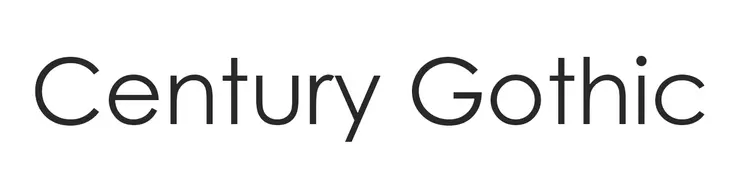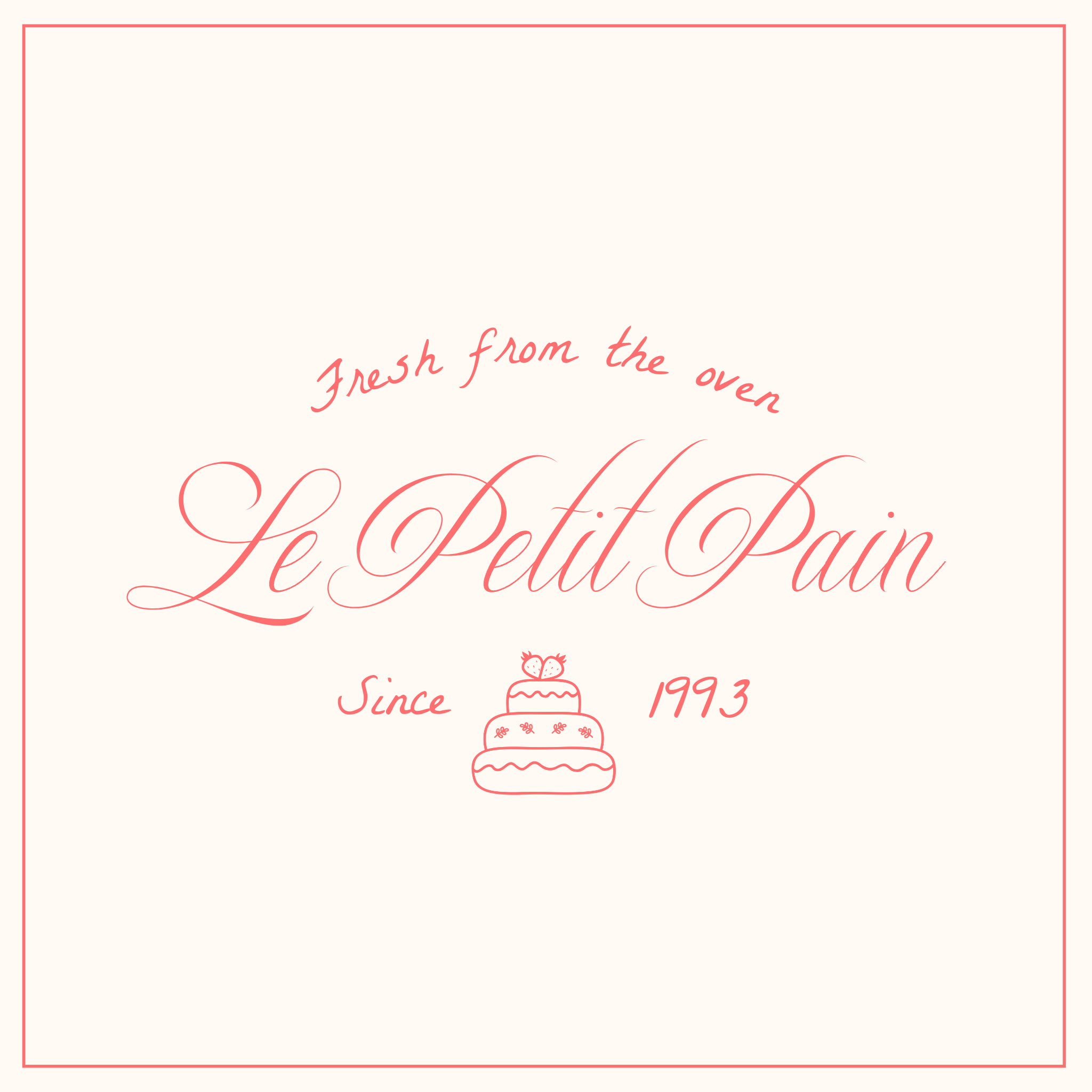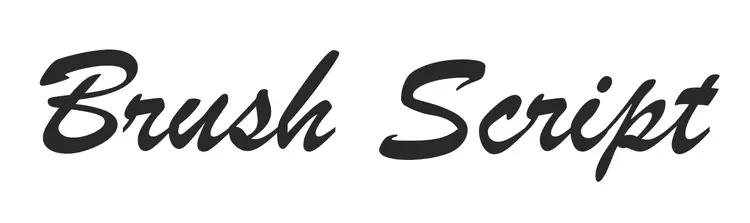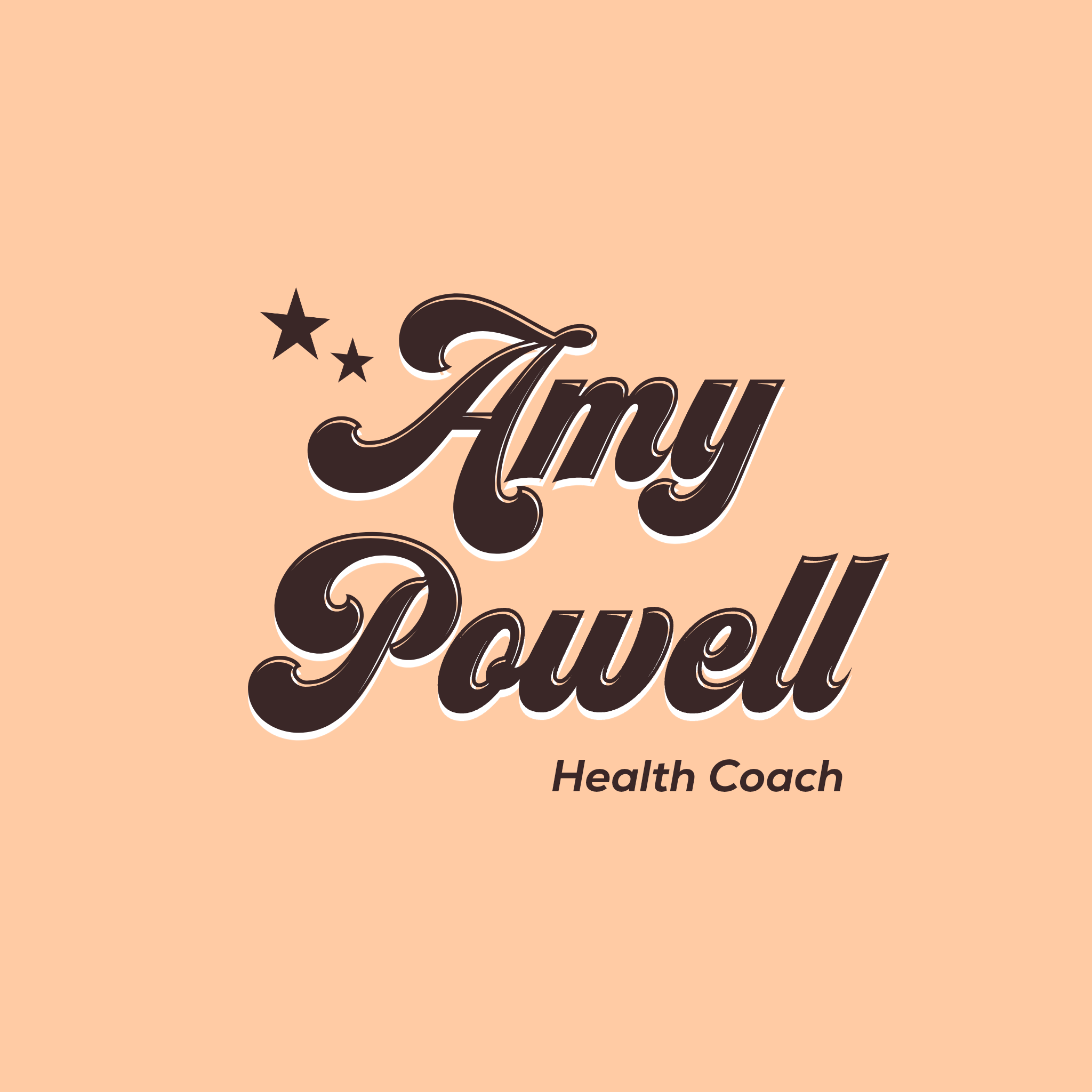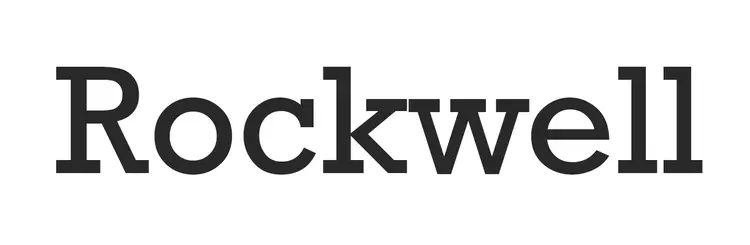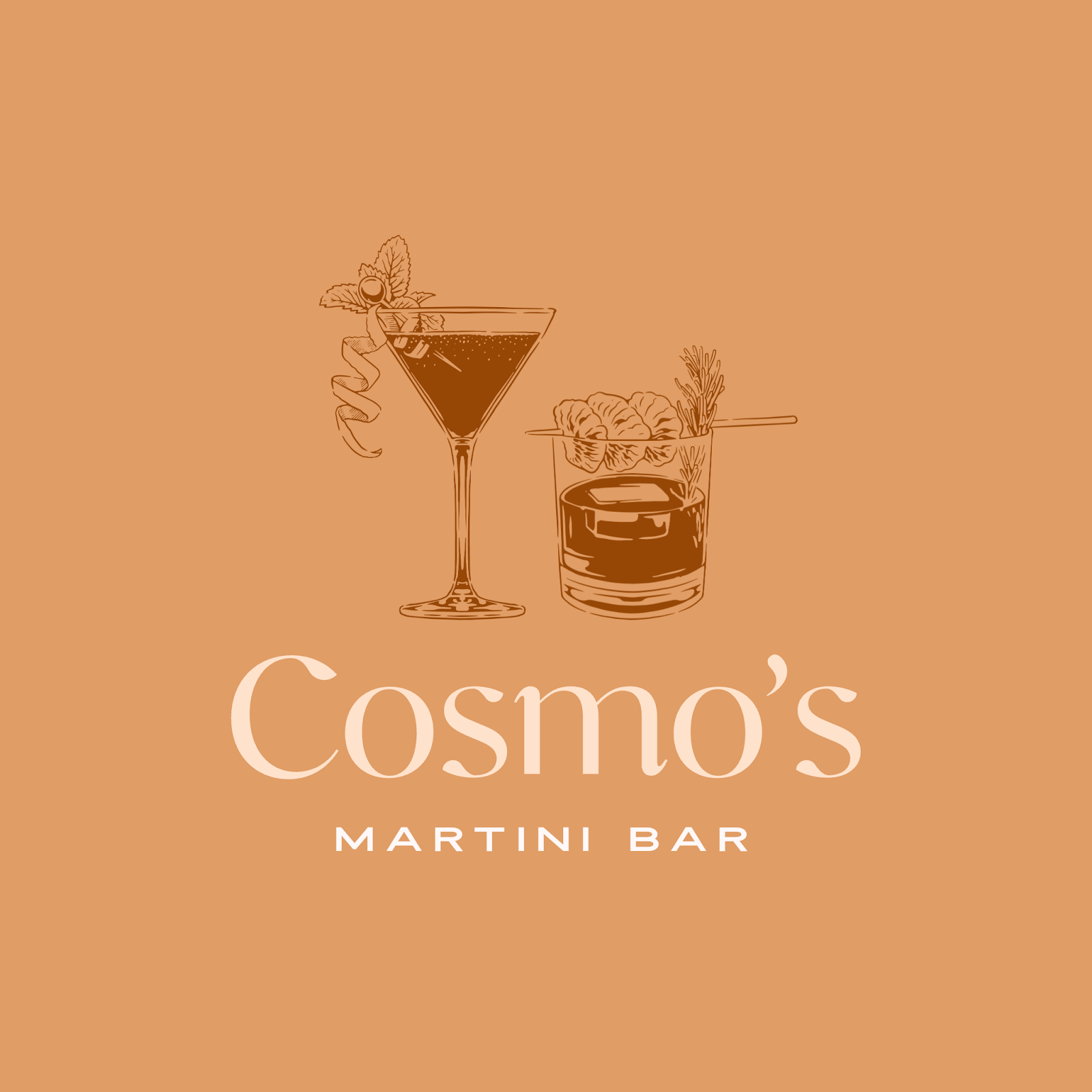
Crear un logo que se quede en la mente de las personas es clave para construir una identidad de marca sólida, y uno de los elementos más importantes para lograrlo es la tipografía.
Elegir la fuente adecuada puede transformar tu logo, hacerlo más reconocible y transmitir el mensaje correcto sobre tu marca.
En este artículo, te compartimos 40 de las mejores tipografías para logos y te damos algunos consejos para que elijas la que mejor se adapta a tu negocio. Ya sea que busques una fuente con estilo clásico, algo moderno o un diseño más artístico, aquí encontrarás un montón de ideas para inspirarte.
Los 4 tipos principales de familias tipográficas empleadas para el diseño de logotipos
Cuando diseñamos un logo, hay cuatro tipos principales de tipografías a considerar: serif, sans serif, script y display. Cada una tiene sus propias características y transmite emociones o ideas diferentes.
A continuación, te explicamos cada tipo con diez ejemplos populares dentro de cada categoría.
Tipografías serif para logos
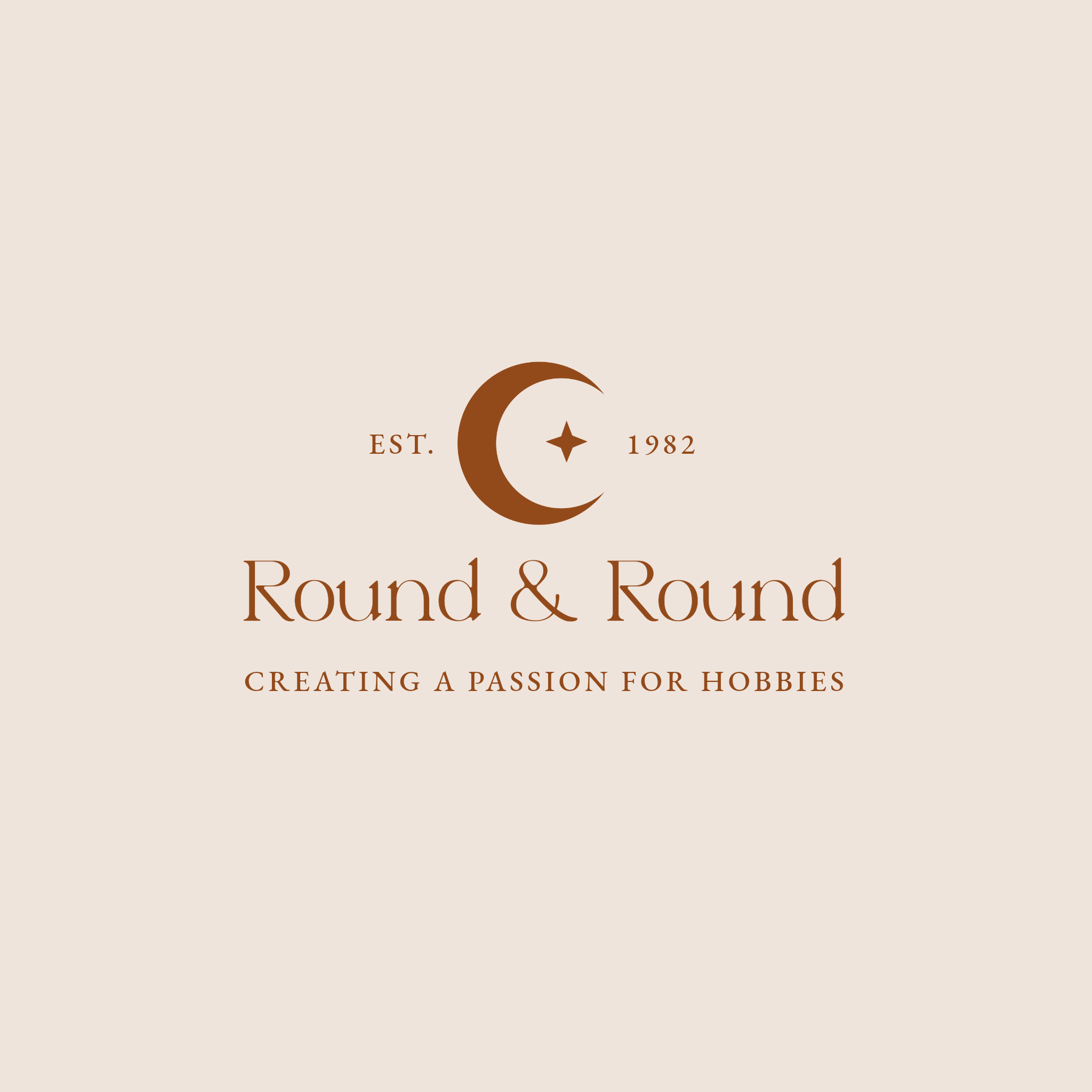
Las fuentes serif son clásicas y elegantes. Se distinguen por tener pequeños remates o líneas al final de los trazos principales de cada letra. Este tipo de letra suele asociarse con la tradición, la confianza y la autoridad. Aquí te dejamos diez ejemplos que lucen increíble en logos:
- Times New Roman: Un clásico entre los clásicos. Conocida por su excelente legibilidad y apariencia formal, esta fuente fue diseñada originalmente para periódicos. Hoy en día, es muy utilizada en contextos académicos y profesionales. Su estructura equilibrada y sus líneas limpias la convierten en una opción segura tanto para textos largos como para títulos.
- Georgia: Una serif moderna, perfecta para pantallas. Con un diseño que favorece la lectura digital gracias a su altura más amplia y formas abiertas, esta fuente combina elegancia con practicidad. Su estilo amigable la hace ideal para sitios web o textos extensos donde la claridad es clave.
- Garamond: Sofisticada y elegante, Garamond es una fuente con historia que muchas marcas de lujo utilizan por su estilo refinado. Sus remates sutiles y curvas armoniosas le dan un aire de distinción que funciona de maravilla en soportes impresos como libros, invitaciones o materiales de alta gama.
- Baskerville: Esta fuente es el equilibrio perfecto entre lo tradicional y lo moderno. Con un alto contraste en sus trazos y un diseño preciso, transmite elegancia y profesionalismo. Es ideal para proyectos editoriales o para marcas con un toque clásico.
- Palatino: Versátil y estilizada, Palatino funciona bien tanto en soportes impresos como digitales. Sus formas amplias y espaciado generoso la hacen muy legible, mientras que su diseño clásico aporta calidez y sofisticación.
- Caslon: Una de las tipografías más tradicionales, usada durante siglos en publicaciones impresas. Su apariencia sólida y confiable la convierte en una excelente opción para libros, revistas o cualquier diseño que necesite proyectar autoridad.
- Century Schoolbook: Con un diseño simple y limpio, esta fuente es famosa por su facilidad de lectura. Se usa mucho en materiales educativos, libros infantiles o textos didácticos. Sus formas redondeadas ayudan a que el contenido sea claro y accesible.
- Bookman: Fuerte y llamativa, Bookman es ideal para titulares o diseños que necesiten captar la atención. Aunque tiene un trazo grueso, no pierde su elegancia, lo que la hace perfecta para carteles o marcas con personalidad.
- Minion: Esta tipografía clásica tiene un estilo cálido y cercano, ideal para todo tipo de proyectos, desde publicaciones impresas hasta digitales. Sus proporciones equilibradas y detalles sutiles la convierten en una favorita para profesionales del diseño gráfico.
- Sabon: Si buscas sofisticación, Sabon es para ti. Con formas elegantes y estructura consistente, esta fuente se usa frecuentemente en materiales impresos de lujo como invitaciones o catálogos. Es una opción clásica para quienes quieren transmitir refinamiento.
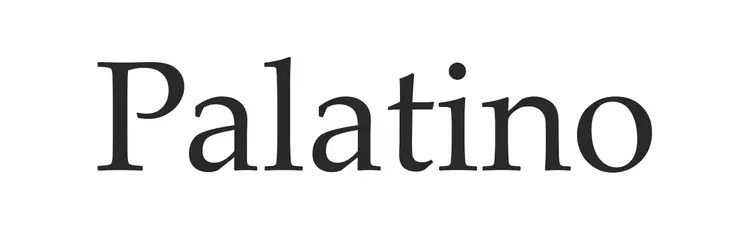
Tipografías sans serif para logos
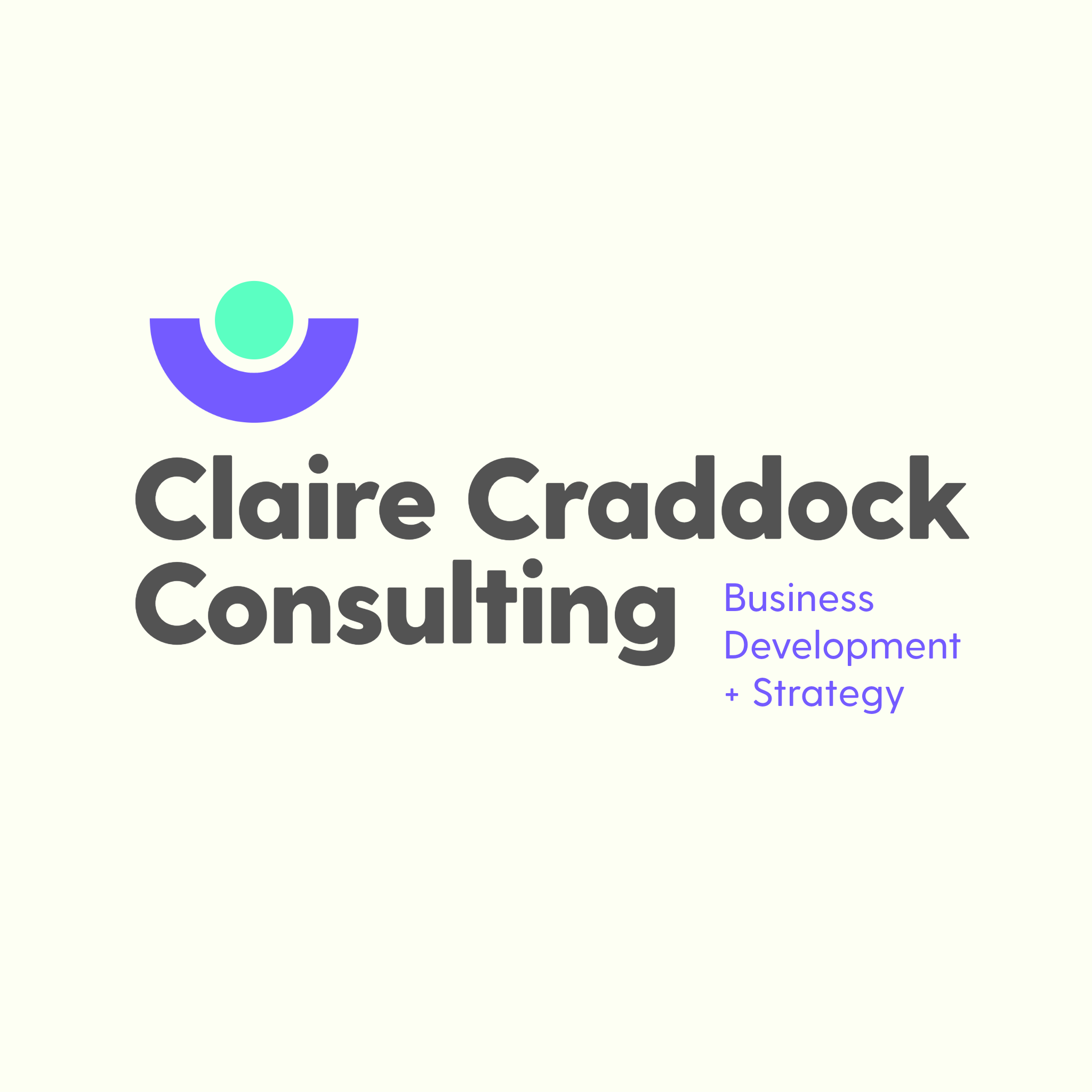
Las fuentes sans serif tienen un estilo moderno y limpio. Se caracterizan por no tener los remates pequeños que sí aparecen en las fuentes serif. Transmiten simplicidad, claridad y profesionalismo, por lo que son muy populares entre marcas tecnológicas y empresas que tienen una identidad visual muy contemporánea.
Aquí te dejamos diez de las mejores fuentes sans serif para usar en logos:
- Helvetica: Helvetica es una tipografía sans serif atemporal, famosa por sus líneas limpias, su neutralidad y su gran versatilidad. Diseñada en los años 50, se ha convertido en una de las tipografías más utilizadas a nivel mundial, gracias a su capacidad para transmitir claridad y modernidad en cualquier medio. Su diseño equilibrado y directo la vuelve ideal para marcas, señalética y comunicación corporativa.
Elige la tipografía ideal para tu logo
Escoger la fuente adecuada para tu logo es un paso clave para construir una identidad de marca que conecte con tu audiencia. Ya sea que estés lanzando un nuevo negocio o rediseñando tu marca, la tipografía correcta puede marcar la diferencia.